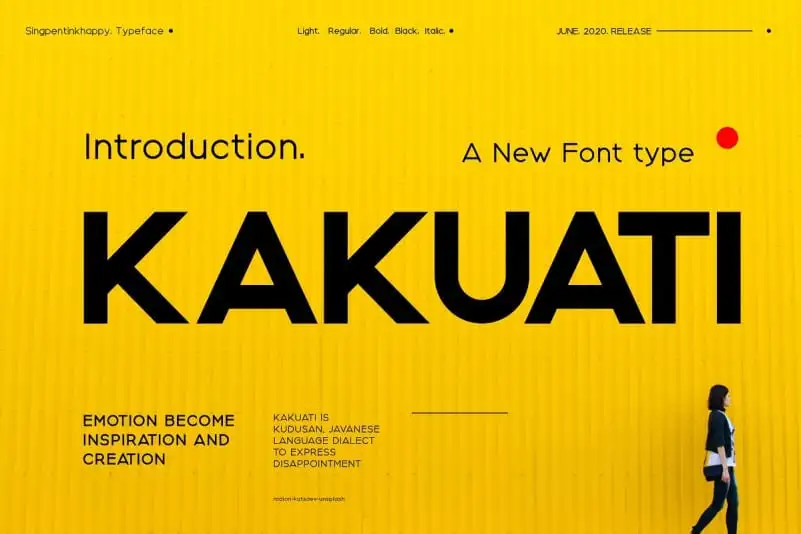
Kakuati Sans Serif é uma família de tipo sem serif com um estilo moderno e carismático que proporciona sensações both atemporais e vintage. Esta fonte estilosa oferece uma viagem visual que vai desde a tipografia mais fina até o sans-serif exageradamente ampliado, criando ambientes de design variados que abrangem múltiplas categorias: marca, comunicação comercial, logotipo, editoriais, moda, música e turismo. Se você está interessado em experimentar design e tipografia, a Kakuati é uma excelente fonte com qual explorar diferentes camadas e ambientes de visualização. Agradeço por dar uma olhada na família de tipo Kakuati.